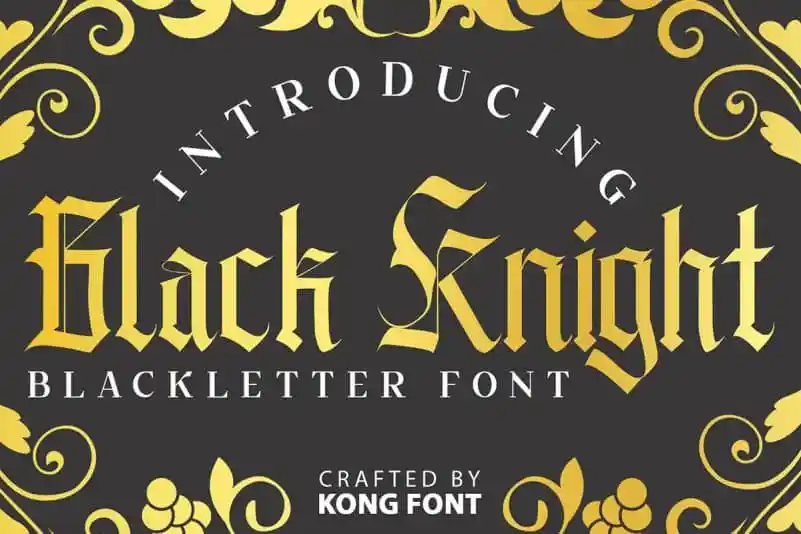
Black Knight Blackletter Font – Download Grátis
A Black Knight Blackletter Font é uma excelente escolha para designers que buscam adicionar um toque único à sua criação, seja ele visual ou tipográfico. Manufacturada pela Kong Font, essa fonte é inspirada nos antigos caracteres do blackletter e colhida de várias referências, incluindo sinalização vintage, logomarcas, selos antiguidades e elementos gráficos antiquados. Essa fonte perfeita para fins de exibição apresenta uma variedade impressionante de formas e traços que remetem diretamente aos tempos passados. Ideal para criações como cartazes, etiquetas, logomarcas, placas de sinalização, camisetas customizadas, capas de livros, decoração ou até mesmo produtos comestíveis, a Black Knight Blackletter Font oferece inúmeras possibilidades criativas. Com uma corrente que se mistura entre o moderno e o antigo, esta fonte traz um toque único às criações mais tradicionais. E a sua natureza vintage permite-lhe ser também usado em tendências futuristas ou inclusão de elementos gráficos clássicos. Uma opção para qualquer designer que deseja introduzir uma nota de originalidade ao seu projeto, seja ele no campo da publicidade ou das artes digitais.